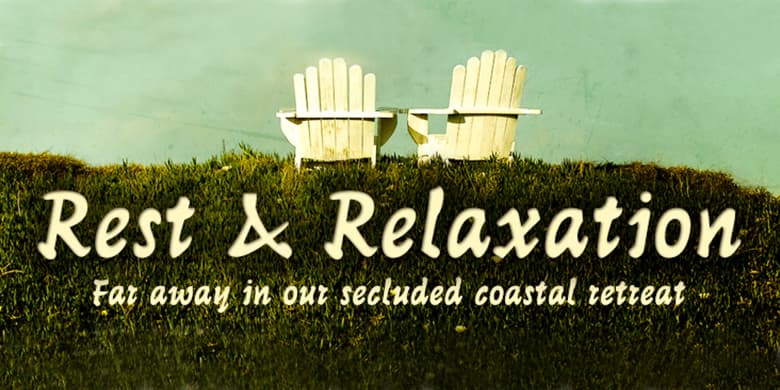
Mustang™
德国设计师克劳斯·萨特(KlausSutter)对野马进行了数字化处理,这是一种20世纪50年代的手写字体,最初由IMREiner(1900-1987)绘制,1956年由D.Stempel AG出版。野马是一种向右倾斜的笔触类型,笔画简单有力。它具有动态性,可以很好地应用于标题的强调。野马具有莱纳笔下的特征。伊姆雷·雷纳是20世纪50年代杰出的插画家、画家和印刷师。
German Designer Klaus Sutter digitized Mustang, a brush script typeface from the 1950s originally drawn by Imre Reiner (1900-1987) and published in 1956 by D. Stempel AG. Mustang is a right slanted brush type drawn with simple and strong strokes. It has a dynamic character, and could be perfectly applied for emphasis in headlines. Mustang has the character of Imre Reiner's handriting. Imre Reiner was a prominent book illustrator, painter, and typographer during the 1950s.